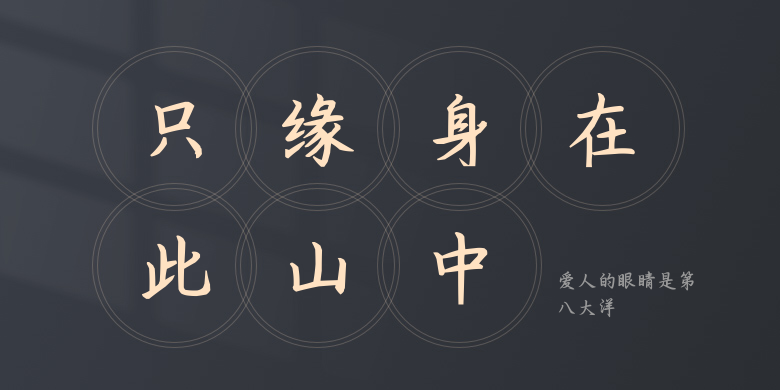
爱人的眼睛是第八大洋
爱人的眼睛是第八大洋,这款字体结构工整、笔画清晰,兼顾美观与易读性,适用于标题、正文、海报、包装、LOGO 等多种场景。字形优雅稳定,风格百搭耐看,适配日常排版与创意设计,让文字呈现更舒适、更具质感。爱人的眼睛是第八大洋一笔一画,皆是细节,以均衡的比例、流畅的线条打造舒适视觉体验,字形端正大气,风格简约现代。无论是商业设计、品牌宣传还是日常排版,都能轻松驾驭,让文字更有格调与力量。爱人的眼睛是第八大洋字体下载。